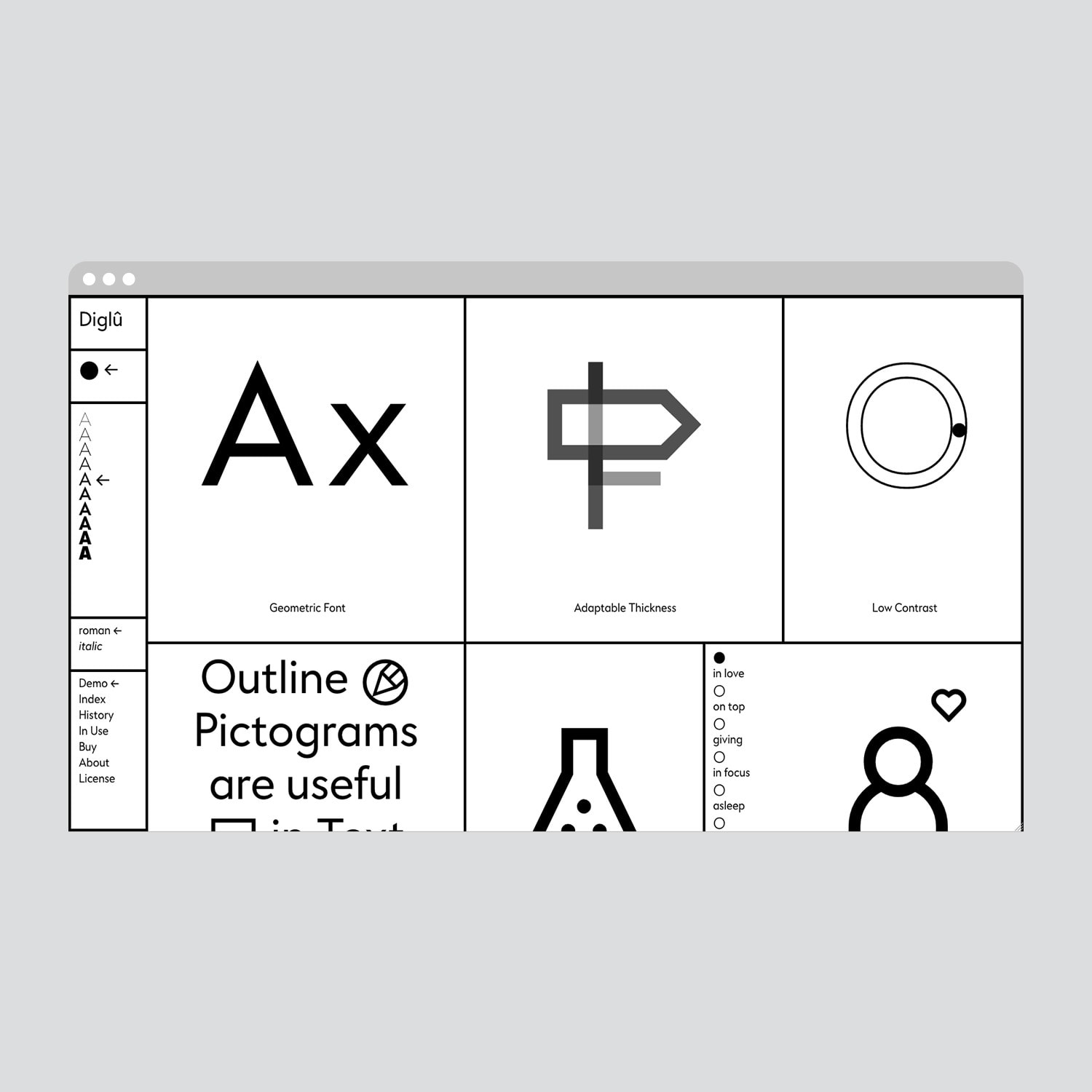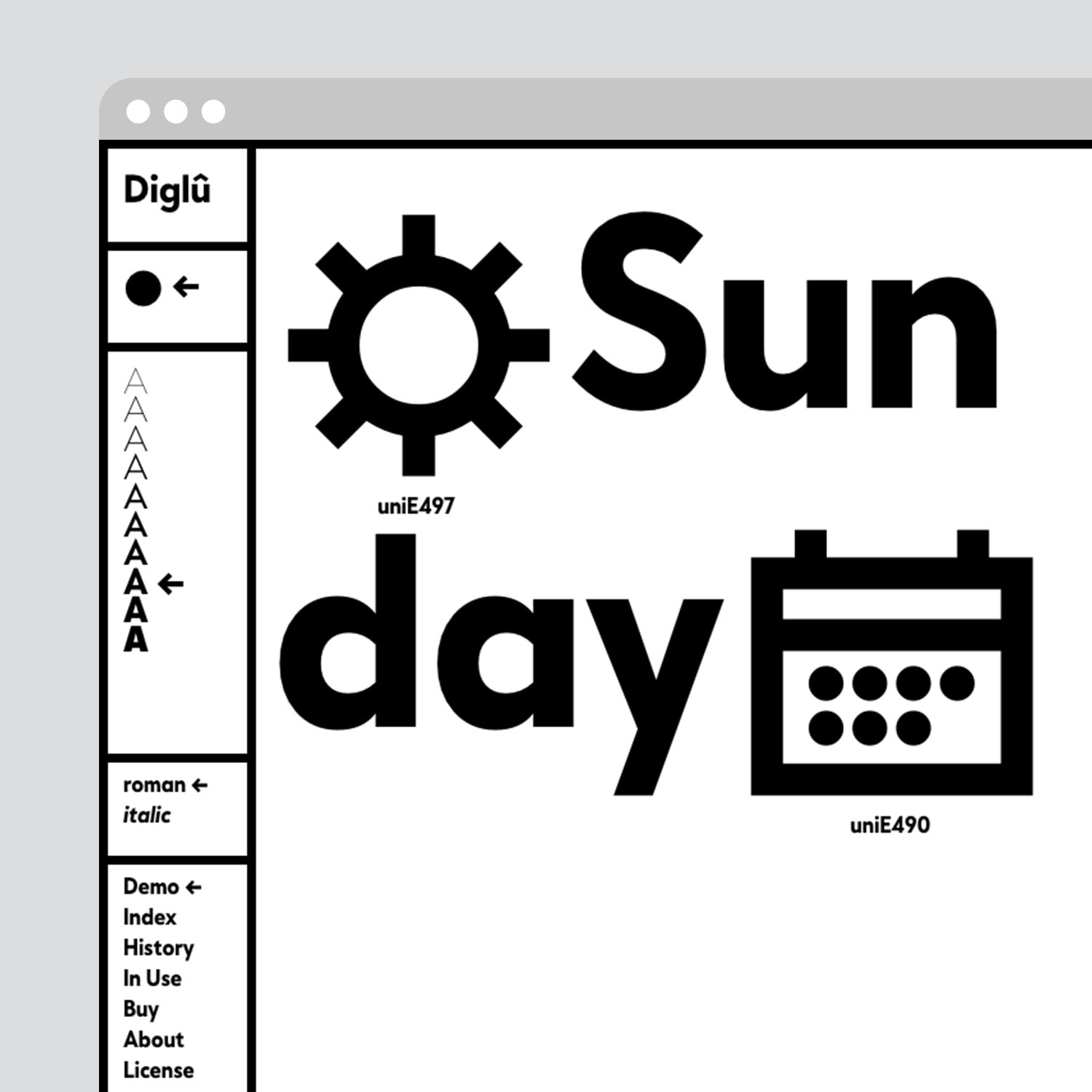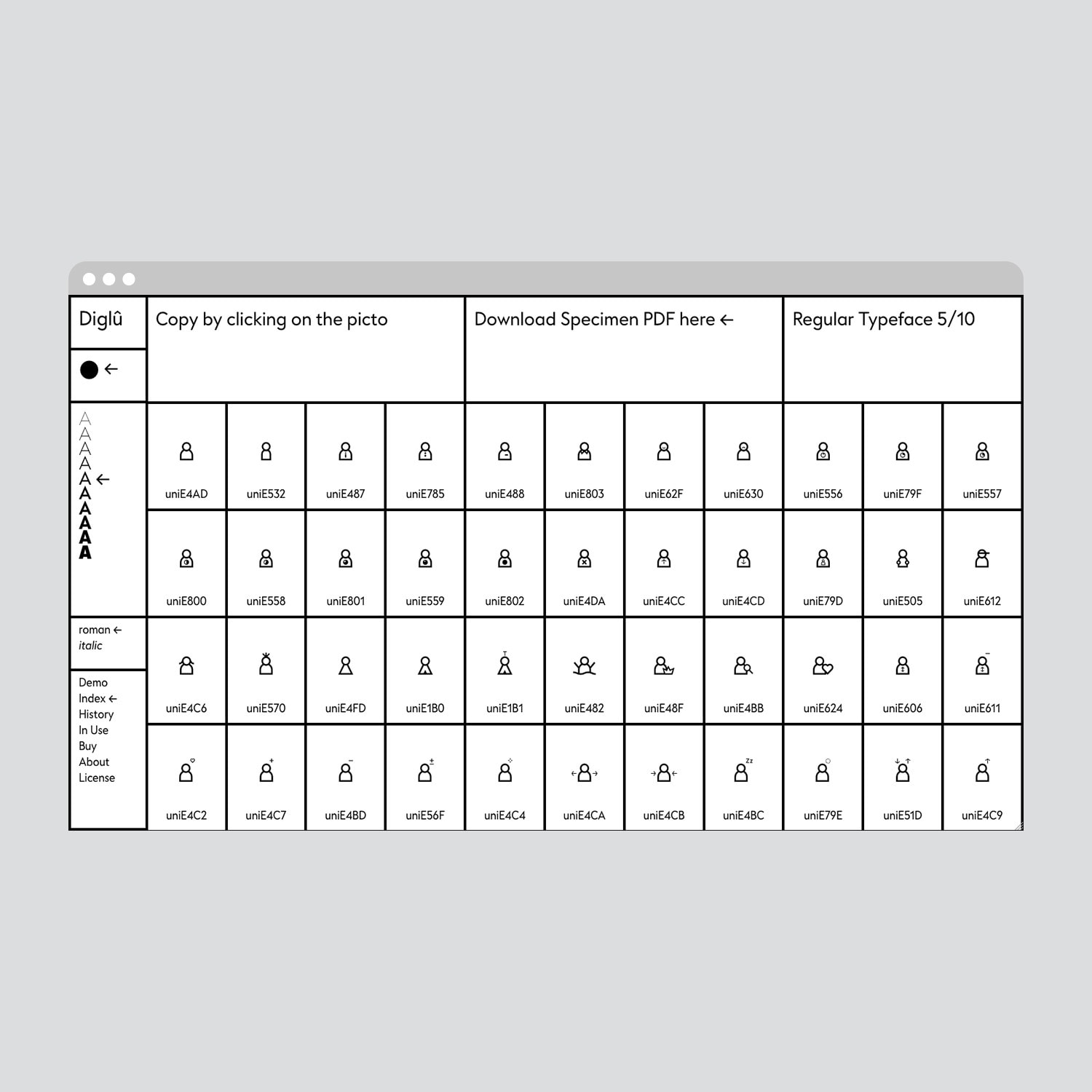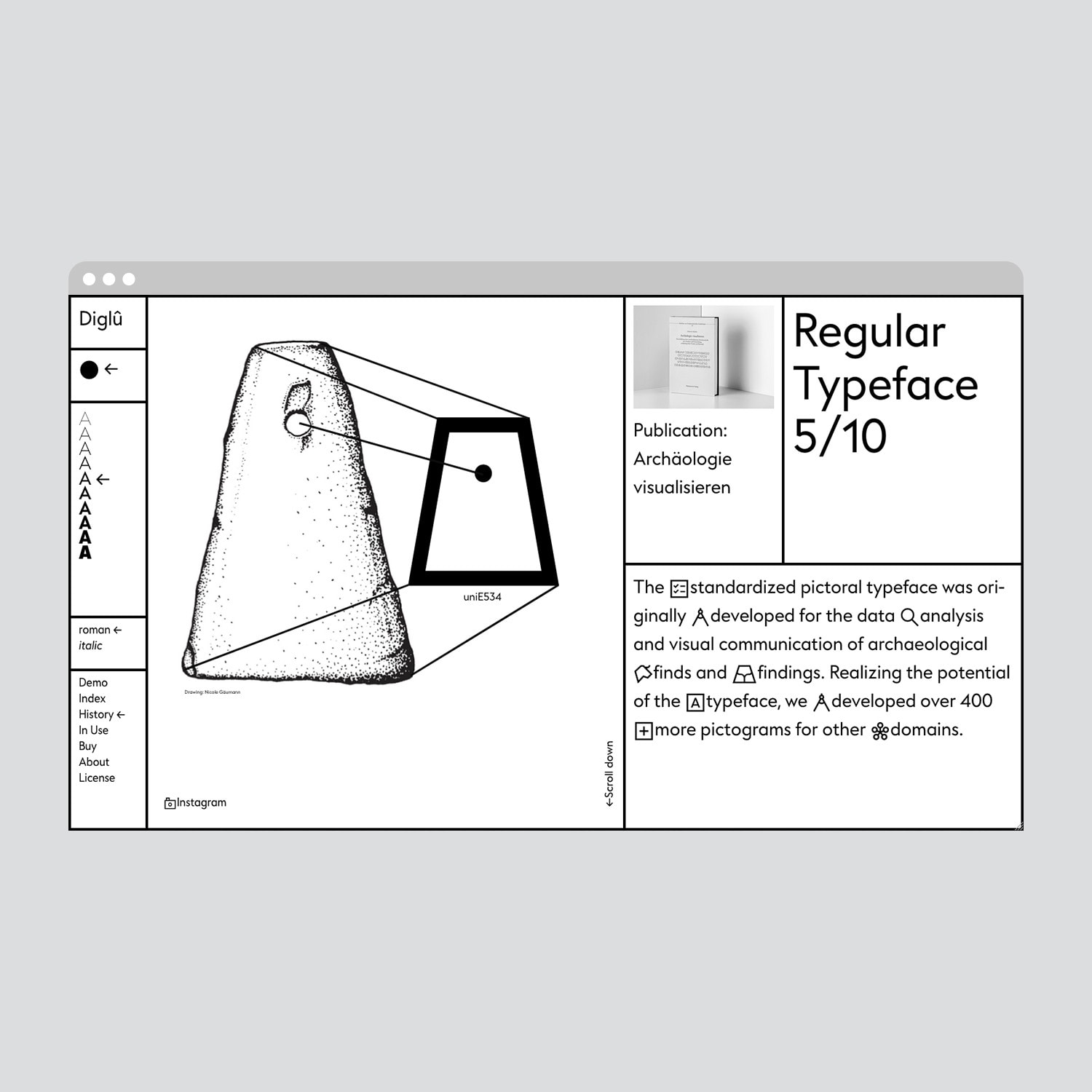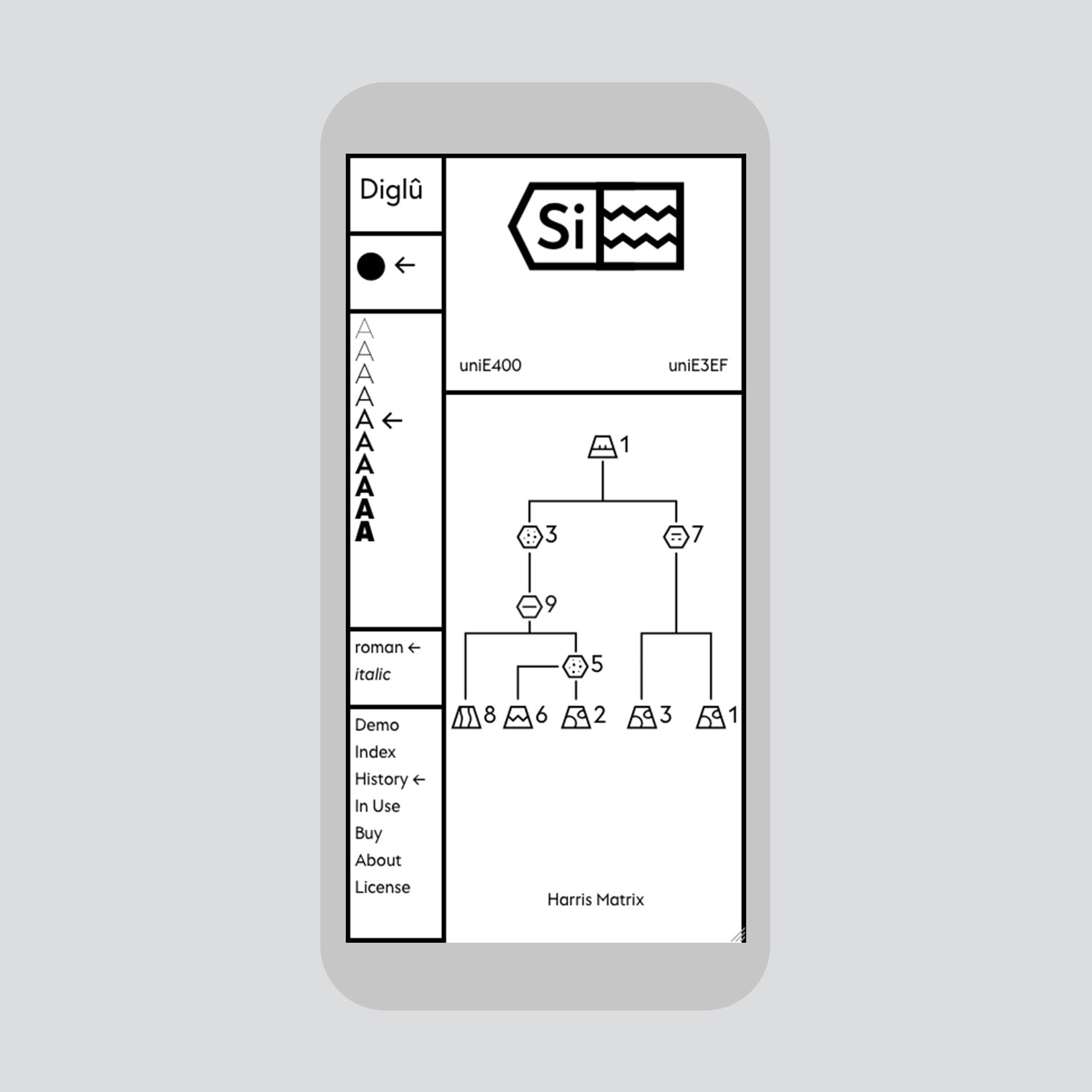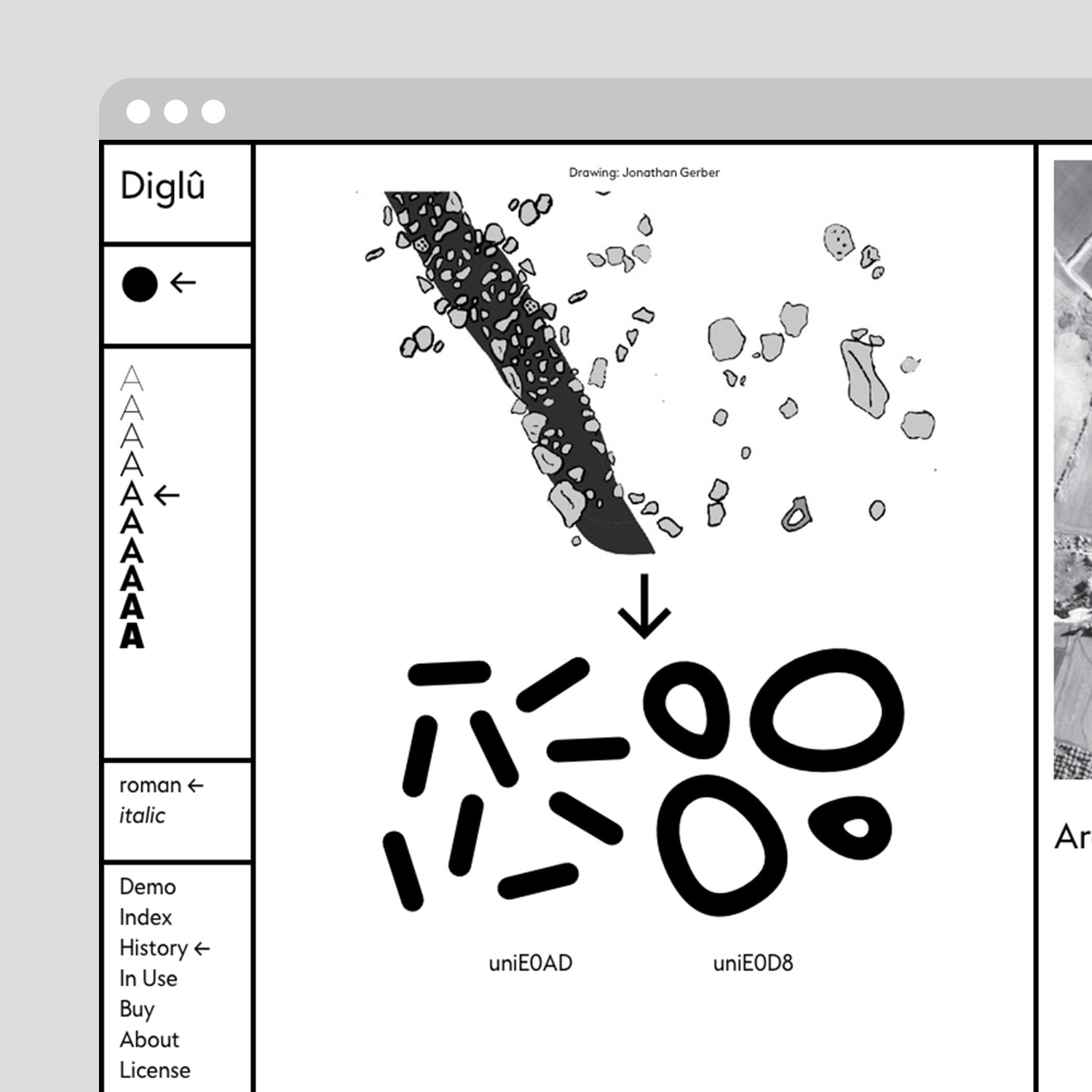
Design und Entwicklung der Webseite diglu.ch, die dem Verkauf der von Emphase kreierten Diglû Font gewidmet ist. Die Besonderheit der Schriftart liegt darin, dass sie Hunderte von Piktogrammen enthält und die Diglû regelmässig durch das Hinzufügen neuer Bildzeichen aktualisiert wird. Die Piktogramme können sowohl in Texten als auch in Diagrammen, Infografiken oder in Mustern verwendet werden.
Die reaktive Darstellung der Website ermöglicht es dem Benutzer, die Schrift in all ihren 20 Schriftschnitten zu testen. Die Seite passt sich an und wird kann von Hairline zu Heavy, in kursiv, Schwarz oder Weiss angezeigt werden.
Der Index listet alle Piktogramme nach Themen auf. Auf diese Weise kann der Nutzer diese mit einem Klick kopieren und in seine Texte oder Dokumente einfügen.
Die Seite «History» dokumentiert die Anfänge des Diglû und das ursprüngliche Entwicklungskonzept für die Archäologie.